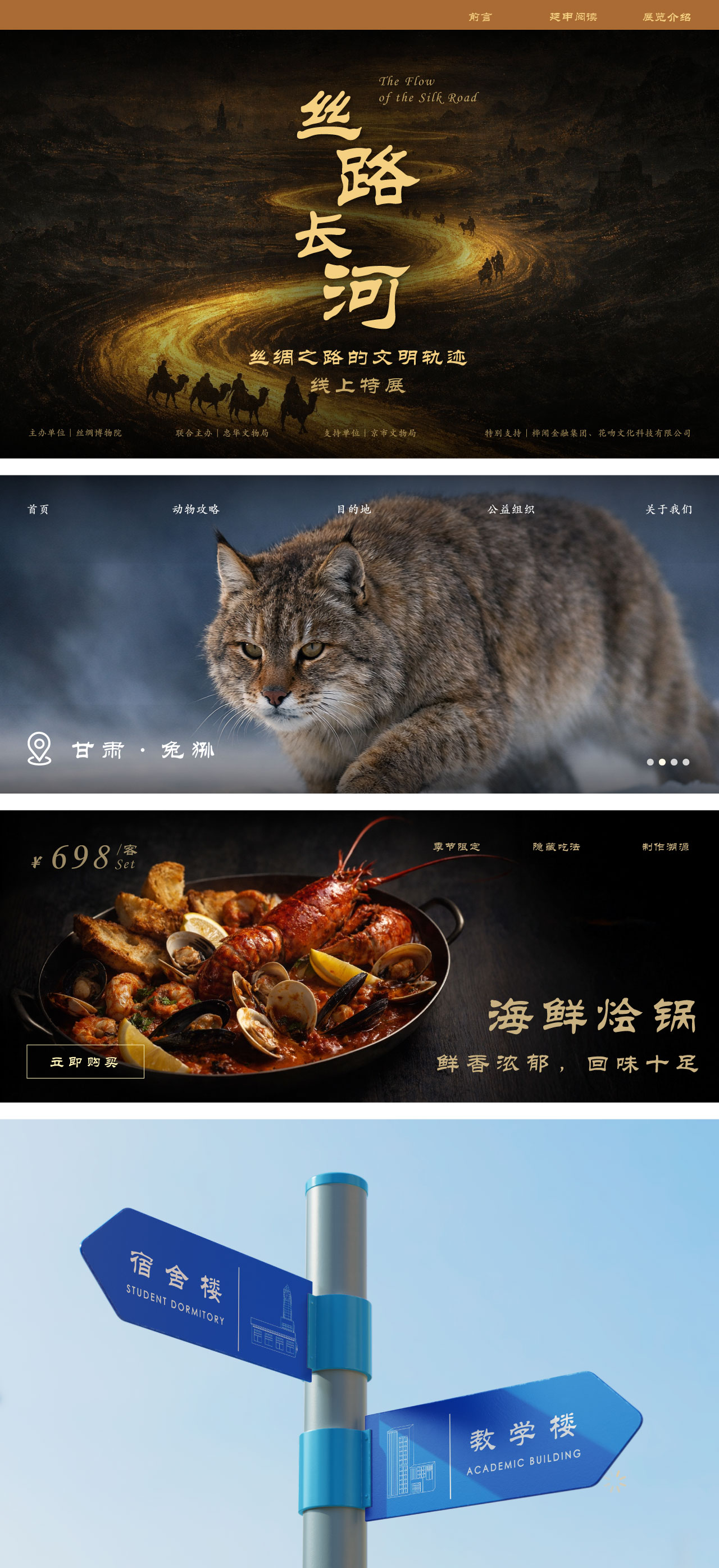
华文隶书 / STLishu / Regular
华文隶书
书法
设计师:
常州华文
字体介绍:
华文隶书在取点制作时对起笔收笔严格的运用了“上则抑,下则扬的起伏特点。横画一波三折,飘逸舒展,竖画内敛遒劲,秀逸平和,古朴庄重。在笔画交错与行笔时,有的凝重,有的舒展,变化较大给人抑扬顿挫的起伏感,整体收放有致、黑白相应、清晰明快、栩栩如生。